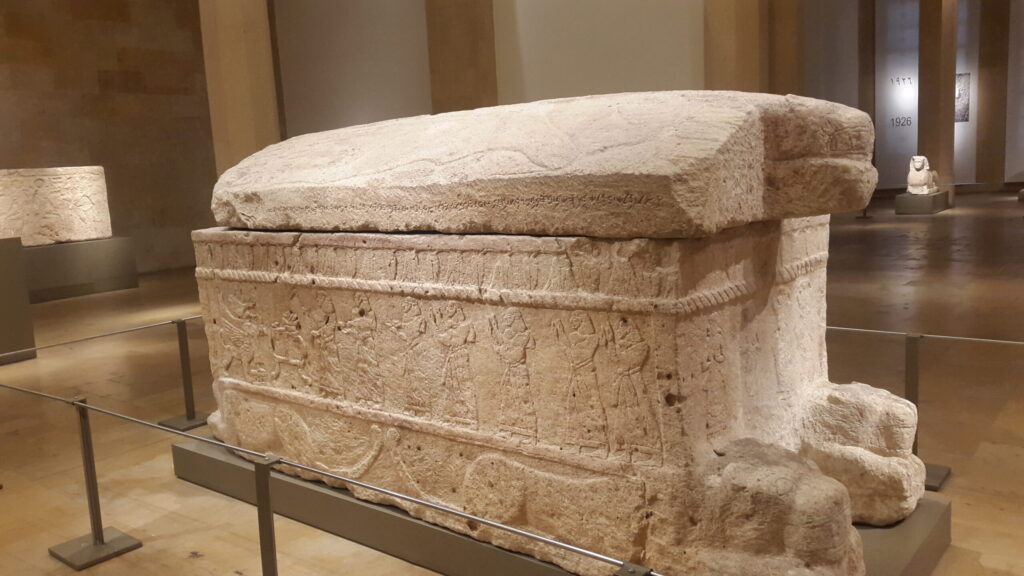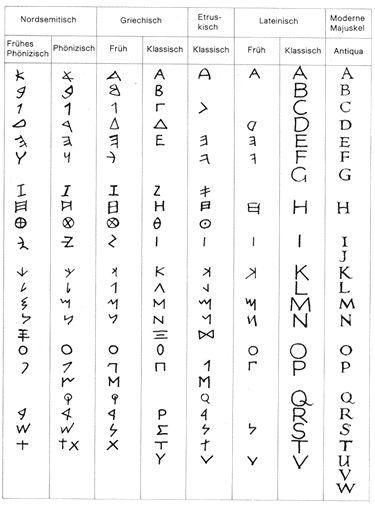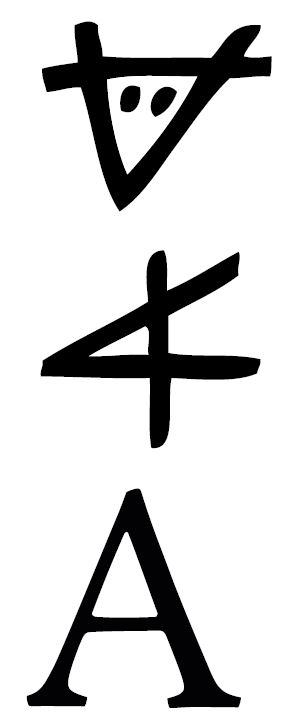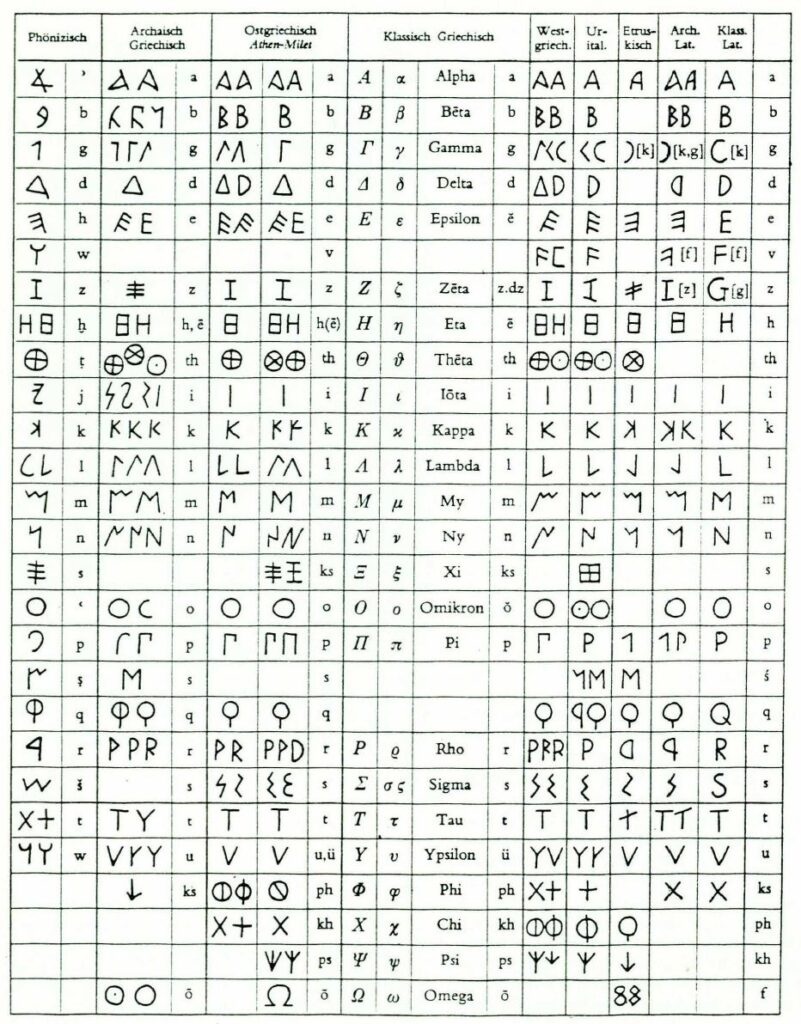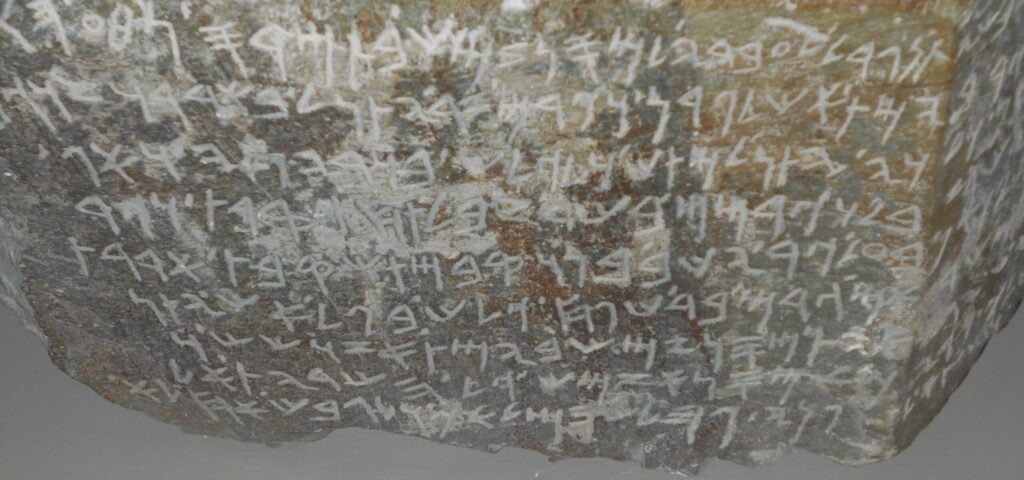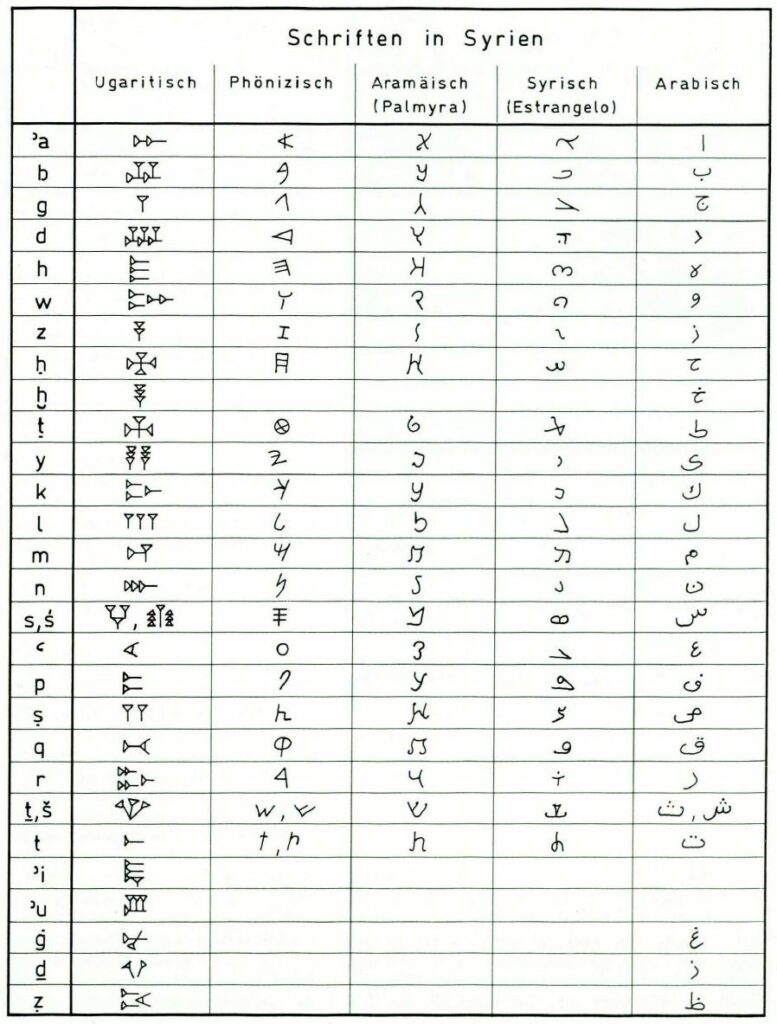
1000 – 1500 v. Chr.
Es deutet vieles darauf hin, dass sich die Phönizier durch die sumerische Schrift sowie die ägyptischen Hieroglyphen inspiriert fühlten, eine eigene Schrift zu entwickeln. Das große Händler- und Entdeckervolk des Altertums aus Phönizien (in der Levante, im heutigen Syrien und Libanon) nutzte als Ausgangspunkt Bilder- und Lautschrift und schuf daraus ein völlig neues Schriftsystem auf Basis von Buchstaben. Die Phönizier stellten alle Konsonanten ihrer Sprache durch 22 einfache Zeichen dar. Damit entstand das erste Schriftsystem, das zunehmend abstrakt und weniger bildlich arbeitete – die Grundlage für unser heutiges Alphabet.
Die Entwicklungsstufen einiger Zeichen lassen sich eindrucksvoll nachvollziehen. So stand unser heutiges „A“ ursprünglich für einen Kuhkopf bzw. einen Ochsen und wurde aus dem Zeichen für die ägyptische Gottheit Hathor abgeleitet. Die Phönizier wandelten dieses Bildzeichen in ein phonetisches Zeichen um, das die Griechen weiterentwickelten und schließlich zu unserem heutigen „A“ formten.
Genau genommen legten die Phönizier damit das Fundament für das griechische, lateinische, hebräische und arabische Alphabet.